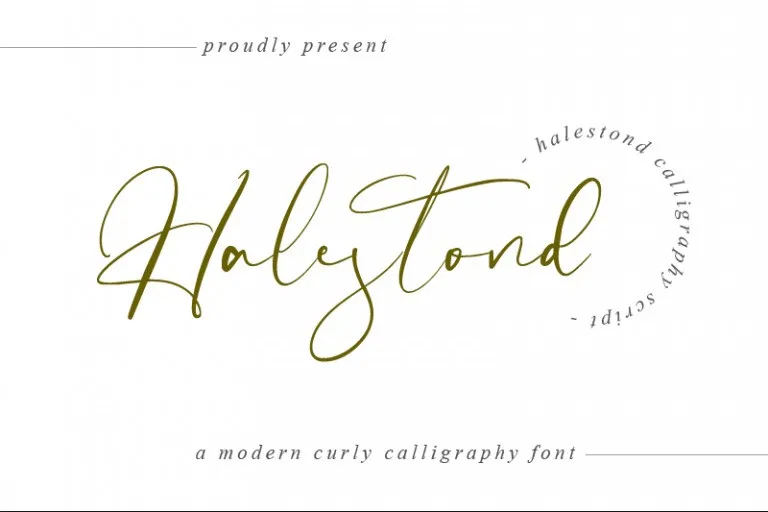
A Halestond Font é uma elegante escolha para quem busca uma fonte script elegante e sofisticada, perfeita para adicionar um toque único a design variado. Desenvolvida pelo designer de fontes Hugefonts, ela se destaca não apenas por sua versão escrita à mão, mas também pela variedade do baseline e pelos traços levemente suaves e detalhados que dão ao texto uma aparência encantadora. Perfeita para uso em cartões de casamento, cartas de agradecimento, selos pessoais, cartazes de boas-vindas, logotipos ou design empresarial, esta font é uma escolha ideal para qualquer projeto que precise de um toque único e autêntico. A Halestond Font oferece alternativas estonteantes, tornando-a não apenas atraente em sua forma original, mas também quando aplicada a diferentes contextos de uso. Ela é perfeitamente adequada para designers amadores e profissionais em busca de fontes que possam ser usadas de maneiras únicas no design, garantindo um visual único que destaca seu trabalho.